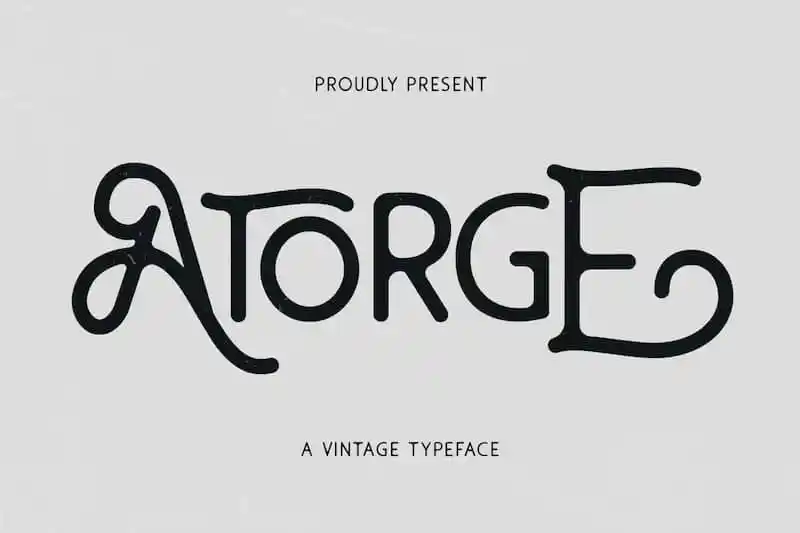
A Atorge Display Font é uma tipografia dinâmica que traz letras maiúsculas e minúsculas, símbolos, alternativas e suporte a múltiplas línguas. Foi criada pelo designer Maulana Creative na 99designs plataforma. Sujeito perfeito para assinaturas, identidade visual, logotipos, textos de tipoográfia, capas de livros ou magazines, cabeçalhos de sites, roupas, embalagens e marcas. A Atorge é uma fonte atraente para diversos tipos de projetos visuais. Combinada com o design moderno da Atorge, seu projeto ganhará um aspecto único e divertido.